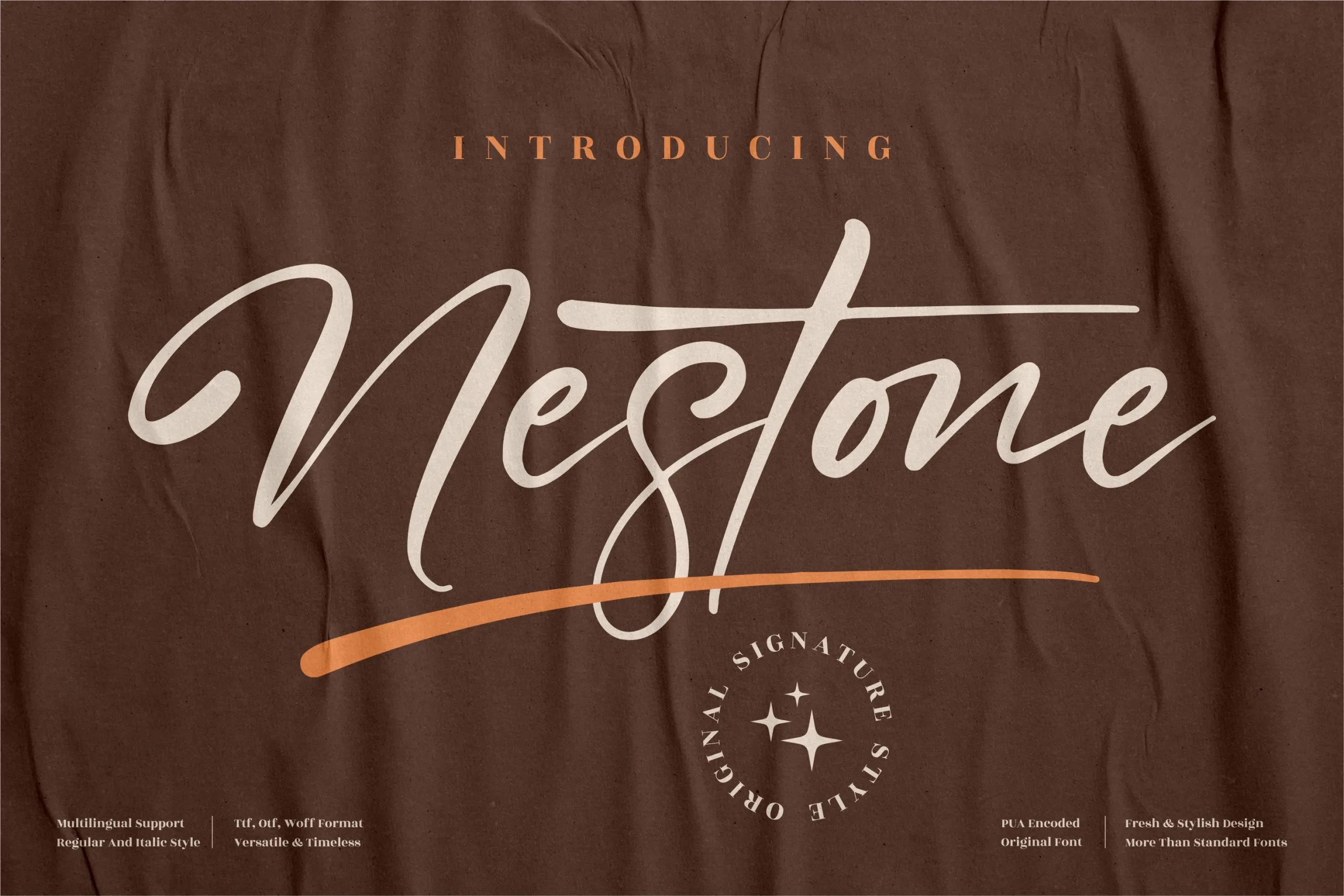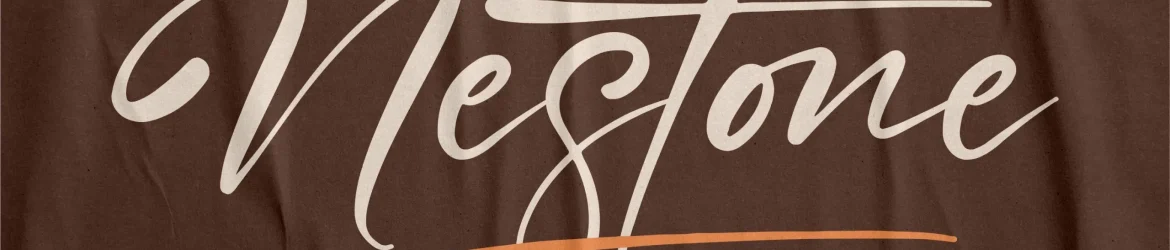
A Nestone Font é uma elegante tipografia cursiva disponível para designers na categoria Handwritten Fonts do perspectype Studio. Esta fonte premium foi criada para oferecer a assinatura perfeita que torna qualquer projeto único e sofisticado. Com Nestone, os designers podem criar identidades visuais memoráveis para marcas de luxo, como embalagens de produto, tags de estoque ou material promocional. Esta font é ideal para personalizar itens como pratos, sacolas de compras e até mesmo mugs. Ela também oferece uma paleta perfeita para expressar mensagens pessoais em cartões de convite, cartazes de eventos especiais ou capas de livro. A Nestone Font não apenas torna seus projetos mais distintivos, mas também adiciona um toque autêntico e elegante que encoraja o consumidor a olhar de novo. Além disso, ela está disponível em diversos tamanhos para atender às necessidades variadas dos projetos de design.